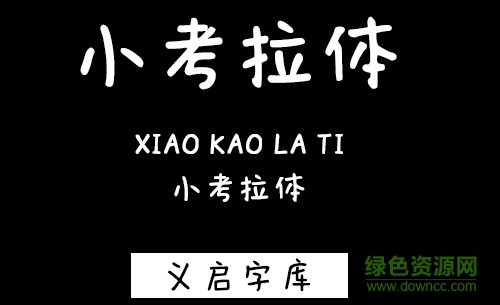
義啟小考拉體是一款非常有特色的義啟字體,這款字體筆畫圓潤(rùn),字形可愛,整體效果非常不錯(cuò),喜歡這款字體的朋友可以來綠色資源網(wǎng)免費(fèi)下載使用!
天生萌物,長(zhǎng)相酷似小熊,生有一對(duì)大耳朵,打一動(dòng)物?
1、拐彎處做出了弧線處理,看起來不死板。
2、重心不穩(wěn),給文字添加了個(gè)性。
3、字體沒有規(guī)律,懶散自由。